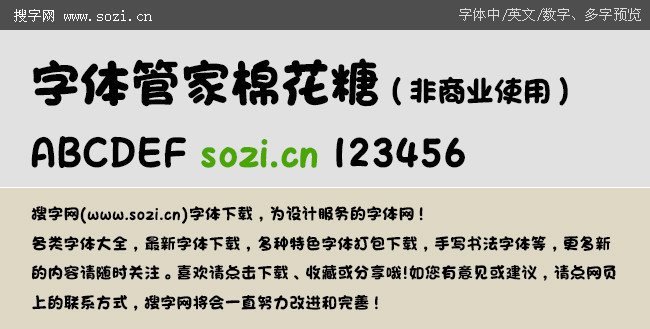
字體管家棉花糖(非商業(yè)使用)
搜字網(wǎng)給大家提供一款字體管家棉花糖(非商業(yè)使用)中文字體下載,該字體是一款是一款可愛(ài)的藝術(shù)字體,隨性且有趣味。適合兒童包裝畫(huà)冊(cè)、書(shū)籍海報(bào)等廣告設(shè)計(jì)應(yīng)用(此字體為個(gè)人非商用版,商用可以聯(lián)系QQ:1006760504)。